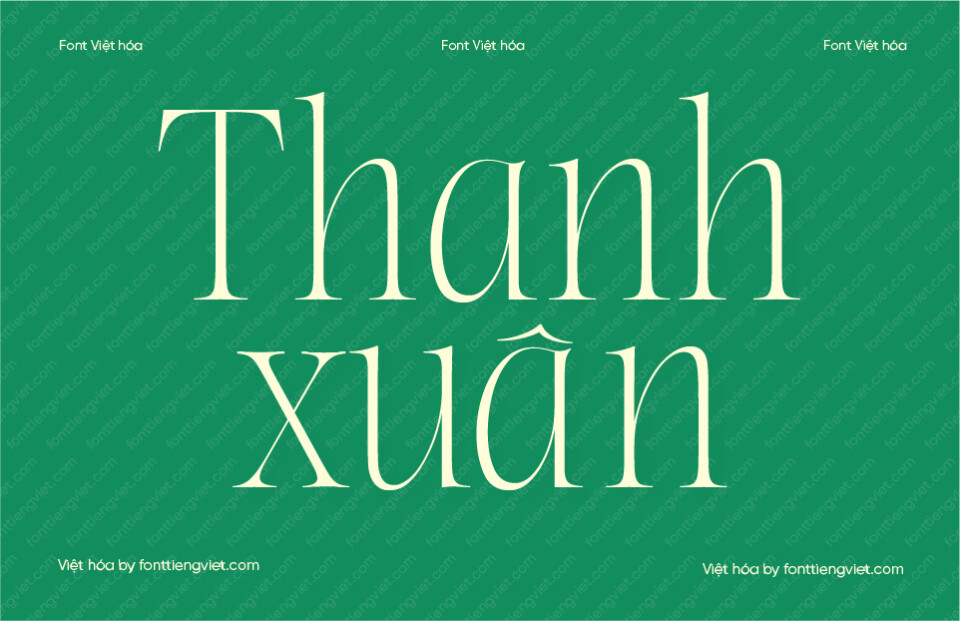
Font Việt hóa 1FTV VIP Aida Light
Trong thế giới đồ họa hiện đại, việc lựa chọn một bộ Font Miễn Phí chất lượng luôn là ưu tiên hàng đầu của các nhà thiết kế và học sinh sinh viên. Một trong những cái tên đang gây chú ý gần đây chính là Font Việt hóa 1FTV VIP Aida Light. Đây là một phông chữ sở hữu nét đẹp thanh mảnh, tinh tế nhưng không kém phần sang trọng, rất phù hợp cho các dự án yêu cầu sự nhẹ nhàng và thanh thoát. Bài viết này sẽ giúp bạn hiểu rõ lý do vì sao bộ font này lại trở nên phổ biến đến vậy trong cộng đồng sáng tạo tại Việt Nam.
Đặc điểm nổi bật của Font Việt hóa 1FTV VIP Aida Light
Font Việt hóa 1FTV VIP Aida Light thuộc phong cách serif hiện đại với các đường nét được tối ưu hóa để hiển thị tốt trên cả nền tảng kỹ thuật số và in ấn. Điểm đặc biệt của phiên bản này là quy trình Việt hóa tỉ mỉ, giúp các dấu câu tiếng Việt được đặt vị trí chuẩn xác, không bị lỗi hiển thị hay mất nét khi gõ các ký tự đặc biệt như “đ”, “ơ” hay “ư”.
Thiết kế thanh mảnh và tối giản
Đúng như tên gọi “Light”, bộ chữ này mang đến cảm giác bay bổng và thoáng đãng cho trang thiết kế. Các nét chữ mỏng nhưng vẫn đảm bảo độ sắc nét cao, giúp người xem dễ dàng tiếp nhận thông tin mà không gây cảm giác nặng nề. Điều này cực kỳ quan trọng trong việc thiết kế các ấn phẩm giáo dục hoặc trình bày tiểu luận, nơi sự rõ ràng luôn được đặt lên hàng đầu.
Tính ứng dụng linh hoạt trong đời sống
Bạn có thể sử dụng Font Việt hóa 1FTV VIP Aida Light cho nhiều mục đích khác nhau như làm tiêu đề sách, thiệp mời, menu quán cà phê hoặc thậm chí là các slide thuyết trình trên lớp. Sự linh hoạt này giúp người dùng tiết kiệm thời gian tìm kiếm mà vẫn đảm bảo được tính thẩm mỹ đồng nhất cho toàn bộ tác phẩm sáng tạo của mình.
Tại sao bạn nên sở hữu bộ Font Việt hóa 1FTV VIP Aida Light?
Lý do lớn nhất khiến Font Việt hóa 1FTV VIP Aida Light được ưa chuộng là khả năng truyền tải cảm xúc. Font chữ không chỉ là phương tiện hiển thị văn bản, nó còn là ngôn ngữ thị giác. Với Aida Light, thông điệp của bạn sẽ trở nên chuyên nghiệp và có chiều sâu hơn. Ngoài ra, việc sử dụng các bản Việt hóa giúp cộng đồng thiết kế Việt tiếp cận gần hơn với các xu hướng typography quốc tế mà không gặp rào cản về ngôn ngữ.
Hỗ trợ tốt cho công tác học tập và giảng dạy
Đối với các bạn học sinh và giáo viên, việc sử dụng một phông chữ đẹp như Font Việt hóa 1FTV VIP Aida Light trong các bài báo cáo hay giáo án điện tử sẽ tạo ra ấn tượng tốt đối với người xem. Một bố cục trình bày sạch sẽ với phông chữ chuẩn sẽ giúp nội dung bài học trở nên lôi cuốn và dễ tiếp thu hơn bao giờ hết.
Kết luận về bộ phông chữ 1FTV VIP Aida Light